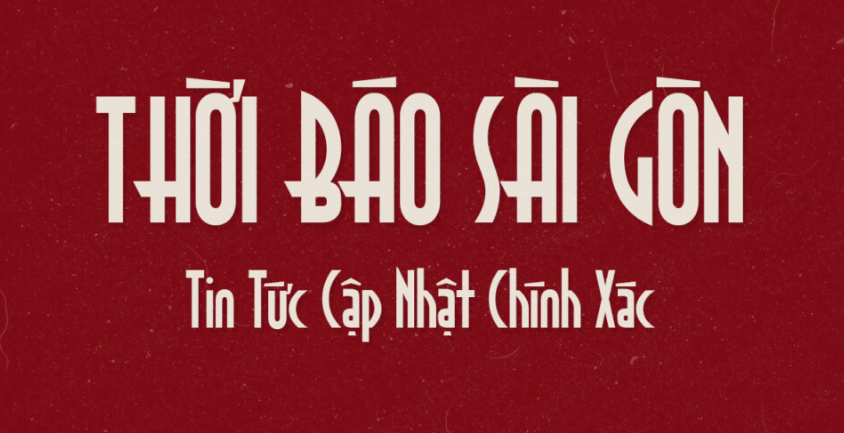
NVN Broadsheet Font là bộ phông chữ có chân (Serif) mang phong cách báo chí cổ điển (Broadsheet Vintage), nổi bật với những đường nét đĩnh đạc, các khối chân chữ dứt khoát và sức nặng thị giác uy quyền của các trang báo in thế kỷ trước. Được đội ngũ NVN tinh chỉnh hoàn thiện hệ thống dấu tiếng Việt, phông chữ này là lựa chọn hoàn mỹ cho các thiết kế tiêu đề nhãn chai bia thủ công, bao bì cà phê rang xay gia truyền, hộp quà tặng phong cách di sản và các ấn phẩm mang hơi thở báo chí hoài niệm. Doozypack.vn cung cấp link tải font NVN Broadsheet Việt hóa miễn phí chuẩn kỹ thuật, giúp bạn sở hữu phông chữ đậm chất truyền thông cổ điển mà không lo gặp bất kỳ lỗi hiển thị dấu thanh nào khi thiết kế in ấn.
Đặc điểm thẩm mỹ độc đáo của NVN Broadsheet Font
Broadsheet không đi theo sự cầu kỳ rườm rà của các phông chữ trang trí; nó tái hiện trọn vẹn tinh thần kỷ luật, sự thẳng thắn và sức mạnh lan tỏa thông tin của kỹ thuật in dập mộc bản (Letterpress) thời kỳ đầu.
Phong cách báo chí Broadsheet thế kỷ 20 đầy uy quyền
Đặc trưng lớn nhất của NVN Broadsheet Font là cấu trúc chữ mang hơi hướng cô đọng (Condensed) theo chiều ngang, giúp tối ưu hóa không gian cho các tiêu đề lớn. Các nét dọc sở hữu độ dày dặn ấn tượng, tạo nên một mảng khối văn bản vững chắc, dứt khoát và mang lại cảm giác tin cậy tuyệt đối cho người đọc. Khi đặt Broadsheet làm tiêu đề trên bao bì, thương hiệu của bạn sẽ ngay lập tức toát lên vẻ chững chạc, uy tín và sự khẳng định về chất lượng gia truyền bền vững.
Chân chữ dứt khoát mang đậm chất in ấn mộc bản (Letterpress)
Phần chân chữ (serif) của NVN Broadsheet Font Việt hóa được thiết kế vuông vức, góc cạnh rõ ràng, mô phỏng lại những khối khuôn chì ép mực trên nền giấy báo thô nhám. Chi tiết cổ điển này mang lại chiều sâu lịch sử độc đáo, giúp bản thiết kế của bạn dễ dàng tạo dựng được phong cách Vintage nguyên bản, khác biệt hoàn toàn so với các phông chữ hiện đại vô hồn trên thị trường.
Ưu điểm nổi bật của bản NVN Broadsheet Font Việt hóa
Khi ứng dụng các phông chữ báo chí cổ điển vào thị trường trong nước, sự chỉn chu về dấu câu là yếu tố quyết định đến tính chuyên nghiệp của bản thiết kế:
- Khắc phục triệt để lỗi dấu tiếng Việt: Phiên bản Việt hóa của NVN Broadsheet đã được đội ngũ thiết kế trau chuốt thủ công từng dấu câu. Các dấu sắc, huyền, hỏi, ngã, nặng được vẽ vuông vức, góc cạnh đồng điệu cùng thân chữ gốc, không gây cảm giác chắp vá hay đè nét làm mất tính thẩm mỹ báo chí.
03 Ứng dụng thực tế của font NVN Broadsheet trong sản xuất bao bì
- Bao bì Cà phê rang xay & Hộp Trà cổ thụ: Nét chữ báo chí cổ điển kết hợp hoàn hảo cùng chất liệu giấy Kraft nâu hoặc phong cách giấy gói tin tức cũ, tạo nên vẻ đẹp mộc mạc và đậm đà phong vị truyền thống.
- Nhãn dán chai Bia thủ công (Craft Beer) & Rượu mạnh: Tiêu đề thương hiệu in bằng font Broadsheet kết hợp kỹ thuật in lụa màu đen trên nhãn decal kháng nước tạo nên diện mạo vô cùng nam tính và đẳng cấp.
- Túi giấy thời trang Vintage & Tiệm Barbershop: Dùng cho tên cửa hàng in trên nền túi giấy tối màu mang lại phong cách cổ điển phương Tây, gợi nhắc đến những quý ông lịch lãm của thế kỷ trước.
- Kiểm soát hiện tượng tràn mực (Dot Gain) tại khe chữ nhỏ: Các khoảng hở bên trong chữ cái (như chữ ‘e’, ‘a’, ‘s’) khá hẹp. Khi in trên giấy Kraft hút mực nhanh, mực có thể bị lan nhẹ làm bít các khe nối. Bạn nên giữ size chữ tiêu đề tối thiểu từ 9pt trở lên để bảo đảm độ sắc nét.